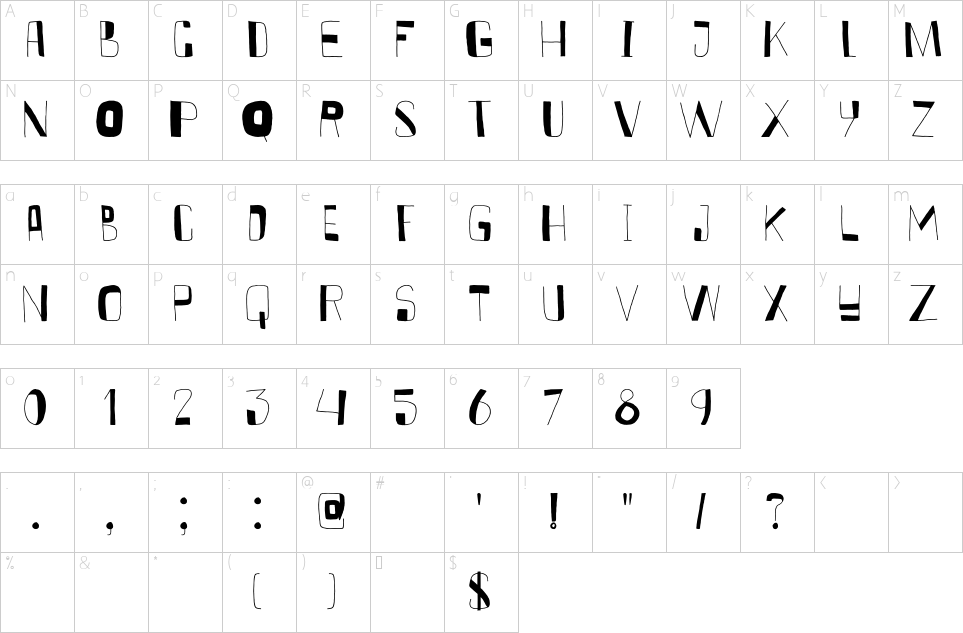
DK Kurkuma é uma fonte moderna e vibrante criada por Hanoded, disponível para download tanto para sistemas Windows quanto Mac. Esta fonte foi especialmente desenvolvida para oferecer um toque especial e único às suas criações digitais. Com seu design fluido e colorido, DK Kurkuma enriquece os textos com uma presença de destaque que certamente chama a atenção do seu público-alvo. Até o momento, mais de 1.413 pessoas já tiveram a chance de experimentar esta fonte gratuita, demonstrando sua popularidade e qualidade. Instalar DK Kurkuma em seus projetos pode ser uma maneira criativa de adicionar um toque vibrante que certamente impressionará seus espectadores.